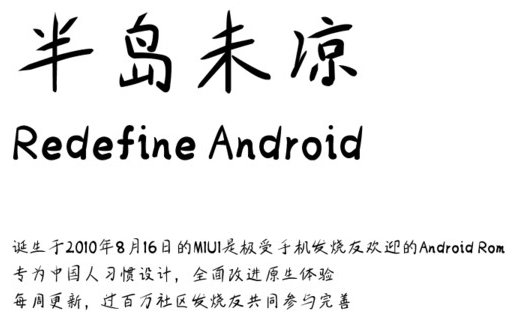
半島未涼字體是手機(jī)qq上發(fā)布的一款特色手寫體,給人十分干凈簡潔的筆觸,讓文字更具清晰度和辨認(rèn)度,十分美觀大方,快來綠色資源網(wǎng)試試吧!
半島未涼字體有著舒適悅目的結(jié)構(gòu),筆觸沉穩(wěn)而干練有力,無多余的修飾,筆畫端正而清爽,是一款視覺交過極佳的藝術(shù)字體,運(yùn)用在包裝設(shè)計(jì)、廣告策劃、藝術(shù)設(shè)計(jì)等方面均有著不錯的效果!